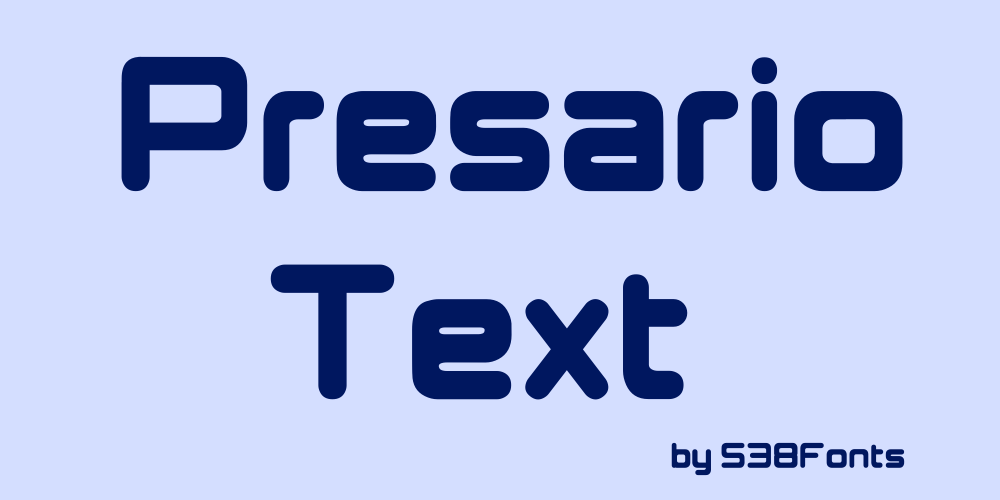
A Font Presario Text é uma versão para texto do famoso “Presario” da categoria Sans Serif, criada pelo designer Hamilton. Inspirada na arquitetura sofisticada e minimalista do logo da Compaq, esta font transmite elegância e simplicidade perfeita para aplicações de texto em diversos ambientes digitais. Com linhas retas, traços finos e uma tipografia clara, Presario Text é a escolha ideal para criar design gráfico moderno e sofisticado. Seja você um designer, editor ou desenvolvedor web, Presario Text pode ajudar a destacar seu texto em qualquer formato de plataforma digital. Ideal tanto para websites quanto para aplicativos móveis, essa font não apenas oferece uma experiência visual única, mas também ajuda a manter uma consistência estética perfeita. Descubra por si mesmo o poder deste design inovador e adicione Presario Text à sua coleção de fontes sem serif para criar conteúdo de texto memorável.